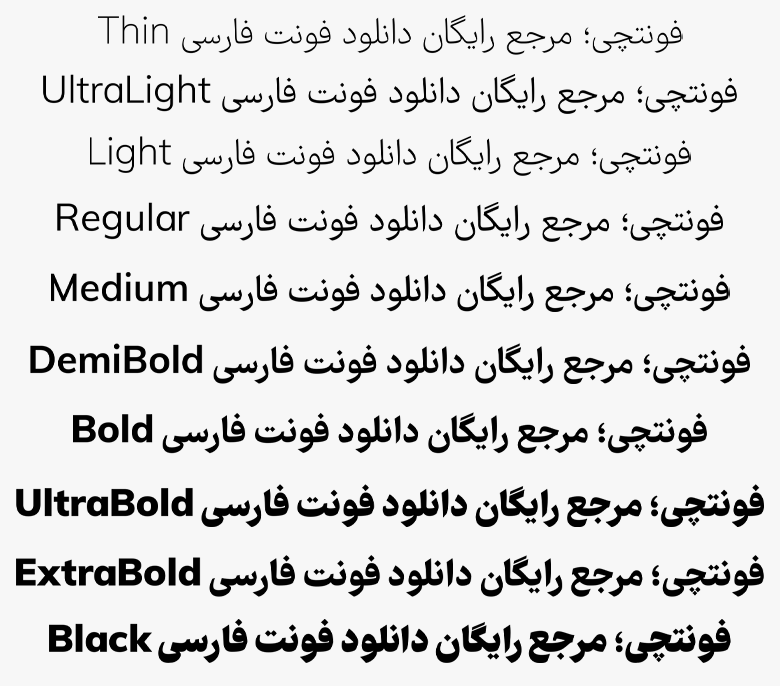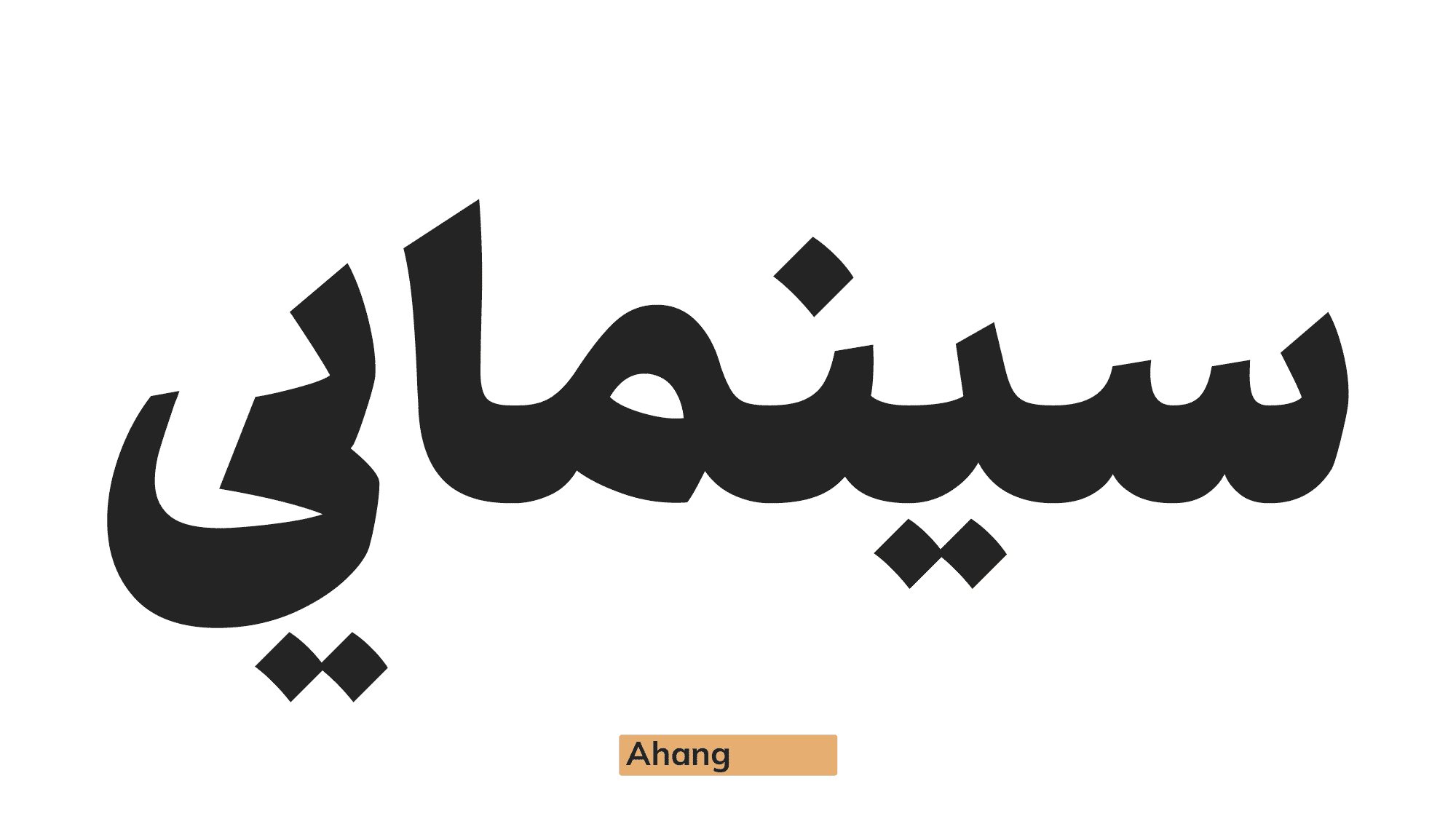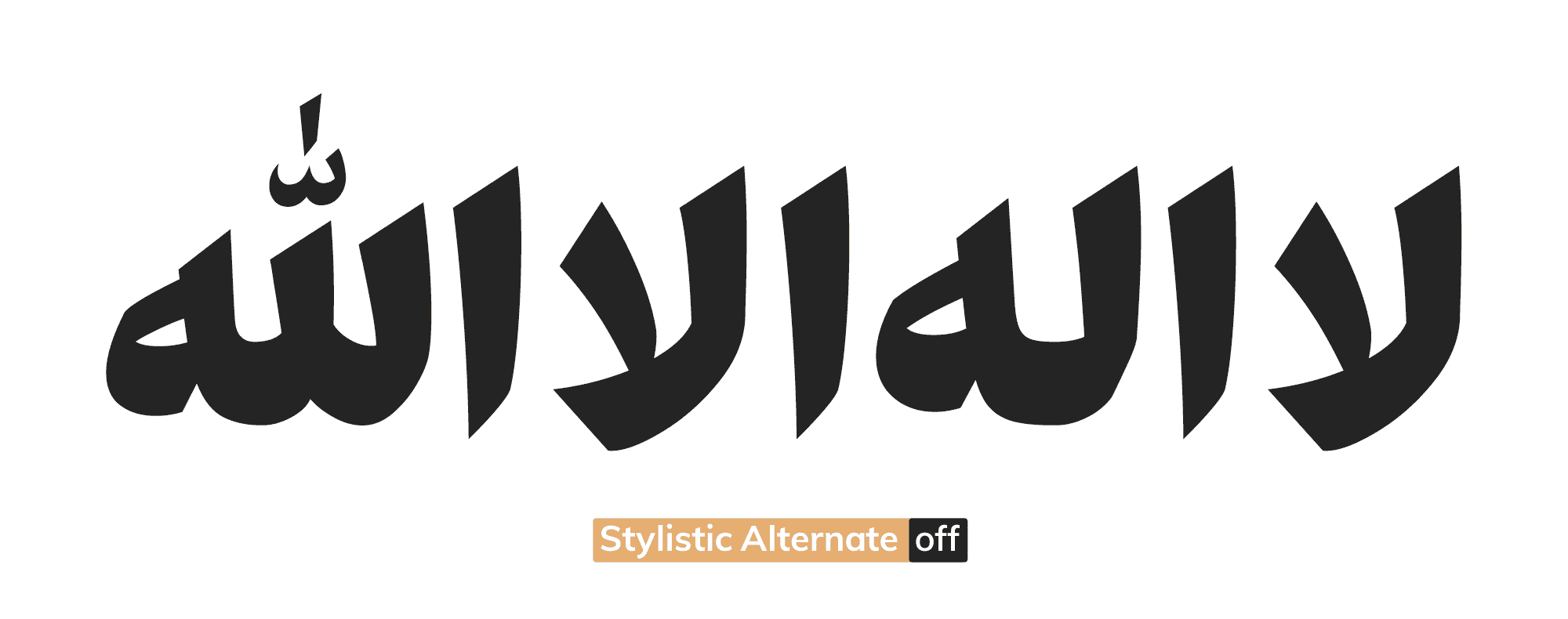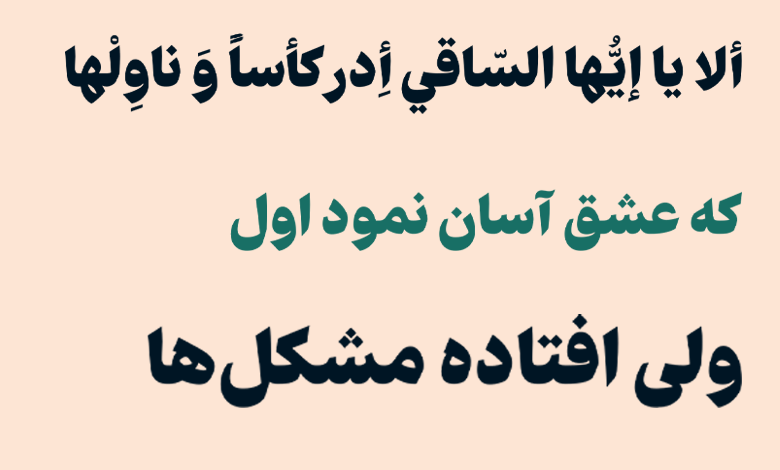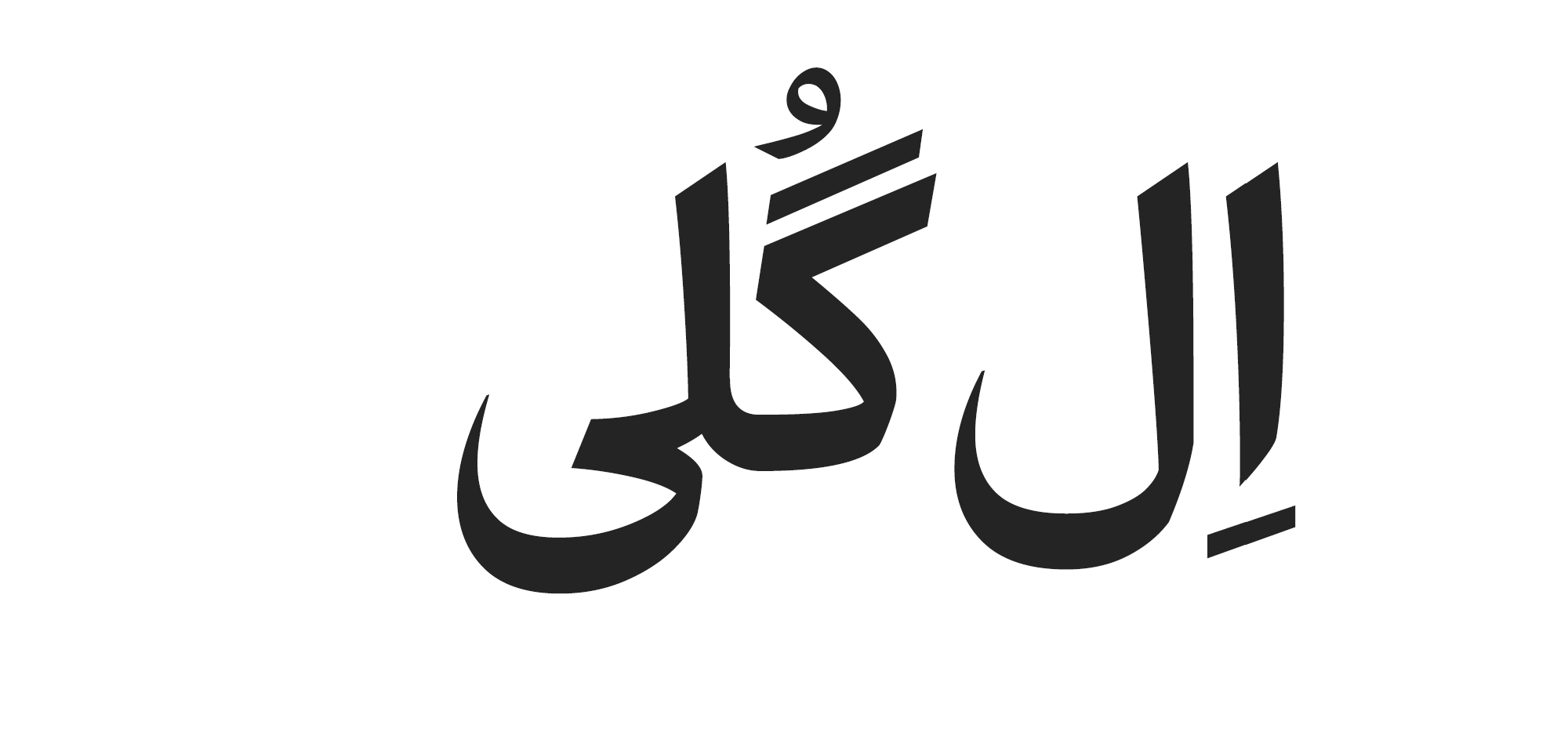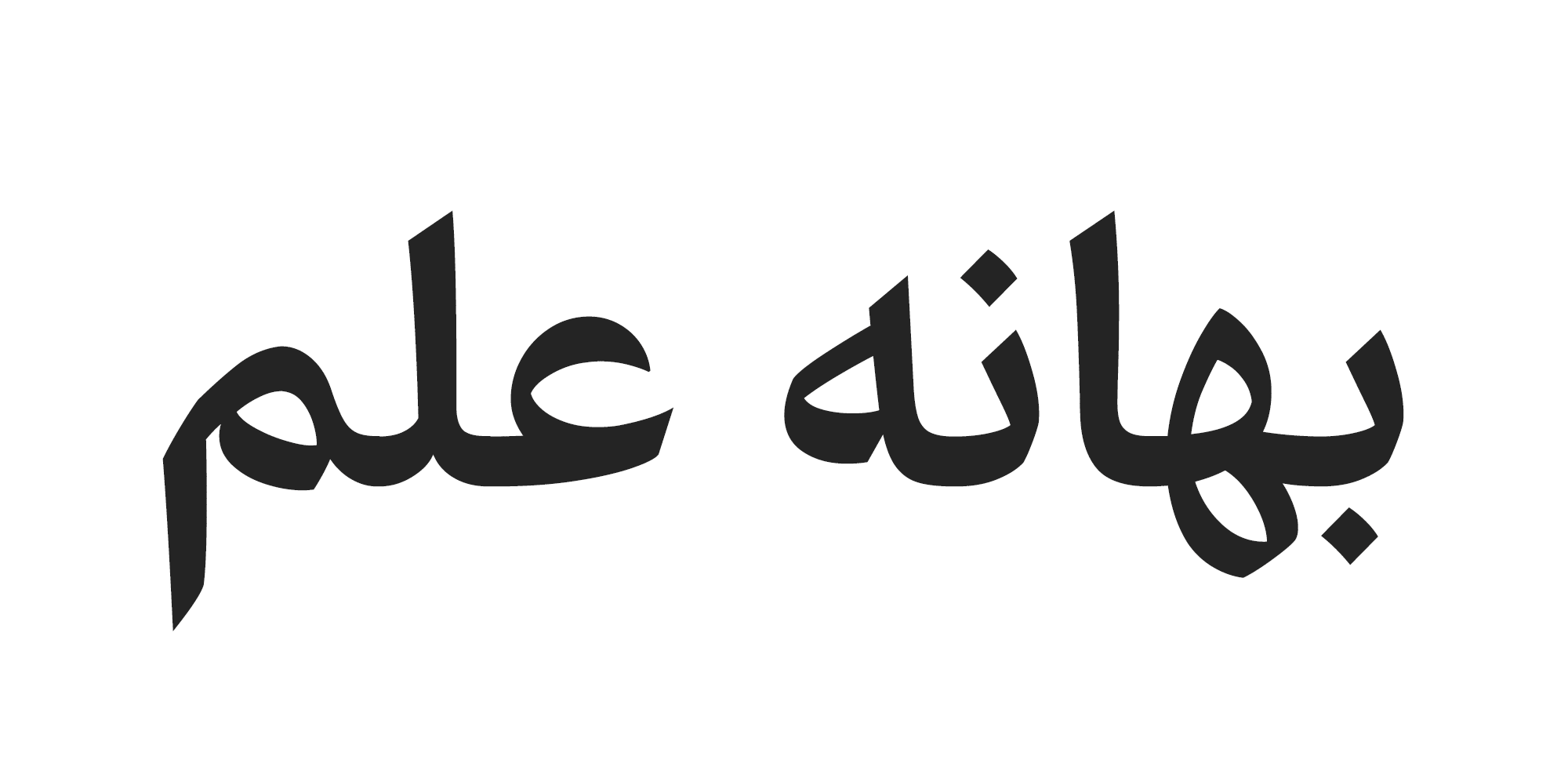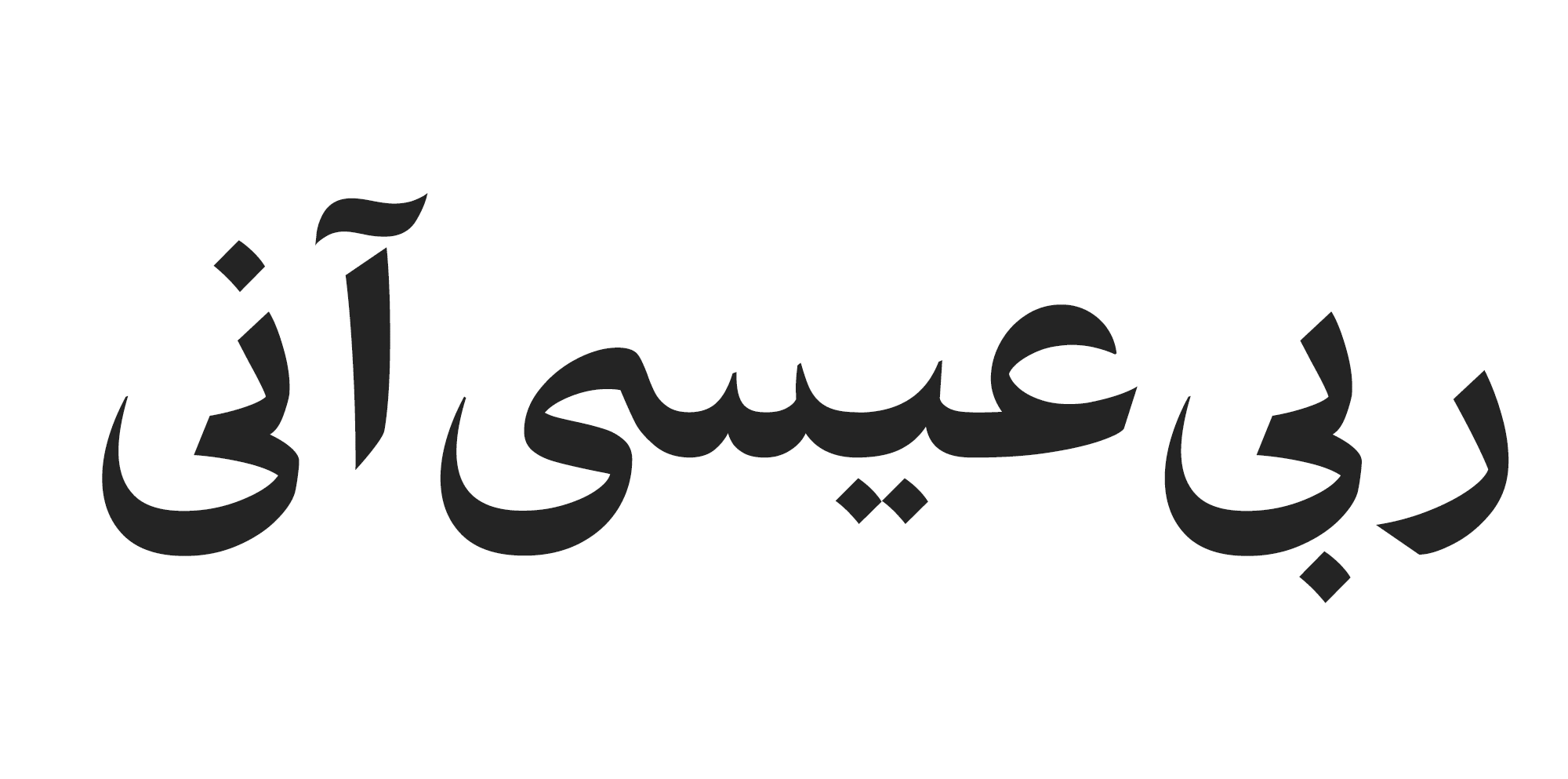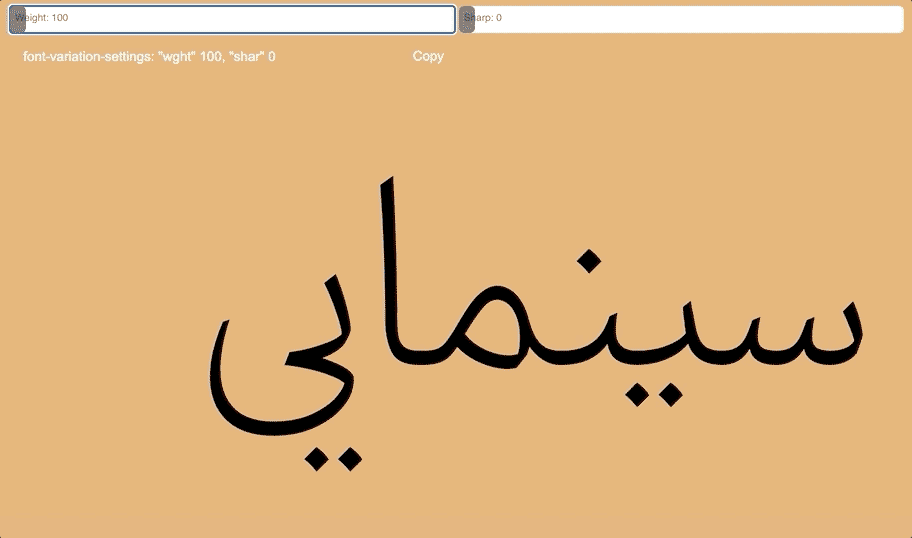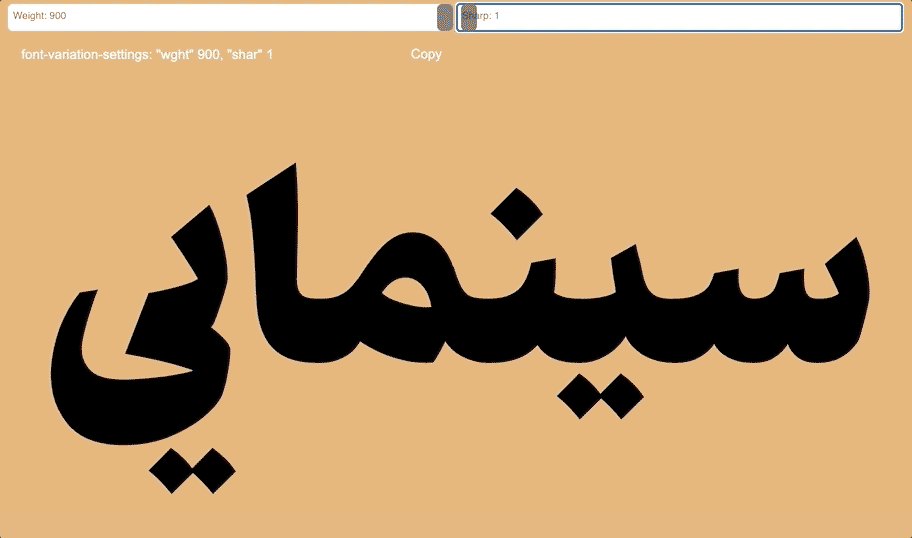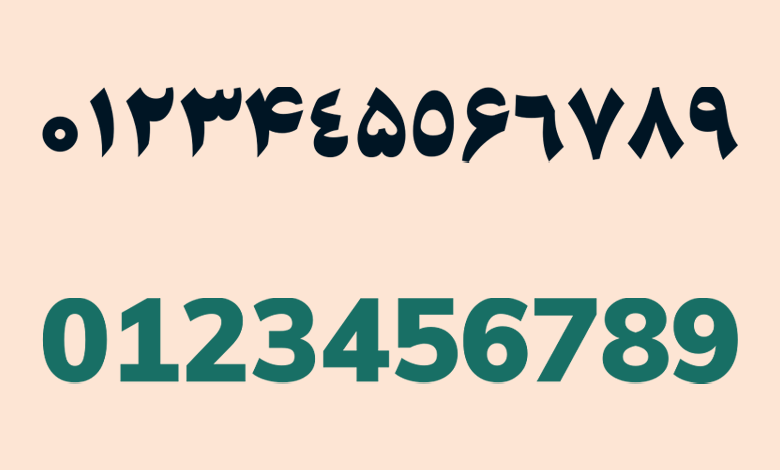
فونت آهنگ (Ahang)
فونت آهنگ (به انگلیسی: Ahang) یکی دیگر از فونتهایی است که توسط مسلم ابراهیمی طراحی شده است. این فونت هم مشابه سایر فونتهای این طراح دارای تنوع وزنی و استایل متنوعی است که میتوانید از آن به عنوان یک فونت متن برای متون طولانی در موارد مختلف صنایع چاپ، وب فونت، کاتالوگ و هر چیزی که دارای متنهای طولانی باشد استفاده کنید.
فونت آهنگ بر پایه خط نسخ طراحی شده که الهام گرفته از فونت فرهنگ است؛ اما با این تفاوت که در این فونت به جای تاثیرپذیری بیشتر از متون مطبوعات، از خوشنویسی دو خط نسخ و ثلث بهصورت ترکیبی الهام گرفته شده است تا در مجموع شاهد فونتی باشیم که هر دو این ترکیبات را در خود دارد.
در ادامه این نوشته از سایت فونتچی به نقد و بررسی فونت آهن خواهیم پرداخت؛ فونتی که جدا از تنوع وزنی ۱۰ تایی خود، امکانات مختلفی را از نظر استفاده از ترکیبات جایگزین، طرههای تزئینی، نسخه وریبل، هم عرض کردن اعداد و نقاط و بسیاری ویژگی دیگر را در خود دارد.
بررسی و دانلود فونت آهنگ (Ahang)
فونت آهنگ در گروه فونت مناسب متن قرار دارد که میتوانید در متون طولانی، بهویژه در وب فونت از این فونت استفاده کنید. با توجه به پشتیبانی این فونت از ۱۰ وزن مختلف، میتوان از وزنهای سنگین هم برای فونت عنوان استفاده کرد.
اگر به دنبال فونتی بر مبنای خطوط خوشنویسی ثلث و نسخ هستید که در هم تنیده شده و یک سمفونی عالی را اجرا کنند، فونت آهنگ میتواند در لیست اولویتهای شما باشد.
سبک طراحی و وزن فونت آهنگ
این فونت از دو سبک از نظر طراحی پشتیبانی میکند؛ آهنگ معمولی و آهنگ شارء؛ فونت آهنگ شارپ حالتی از سبک دوم این فونت است که زمانی که از نسخه Sharp استفاده کنید، اصطلاحا تغییراتی را در کنتراست فونت لحاظ خواهید کرد.
در فونت آهنگ معمولی دندانهها و انتهای حروف تیز نبوده و همان حالت نرم را مثل هر فونت دیگری دارند. اما وقتی حالت شارپ را فعال کنید، دندانهها و انتهای حروف تیز و برنده خواهند شد.
از این نظر فونت آهنگ دارای دو سبک طراحی است که به شما امکان تغییر کنتراست فونت را خواهد داد. این ویژگی را در نرمافزارهای گرافیکی از طریق تنظیمات opentype میتوانید اعمال کنید و برای استفاده در نسخه وب کافی است از تنظیمات متغیری که برای نسخه وریبل قرار داده شده بهره ببرید.
یکی از قابلیتهایی که در خط خوشنویسی ثلث و نسخ وجود دارد، استفاده از طرههای تزئینی است که روی حروفی مثل «ا، ل، لا، ک، صـ، ط» وجود دارد. در این فونت این قابلیت قرار داده شده که بتوانید از این ویژگی نیز استفاده کنید.
برای استفاده از این حالت کافی است در نرم افزارهای گرافیکی با استفاده از تنظیماتی که در Open Type وجود دارد از حالت Stylistic set استفاده کنید.
پشتیبانی از ۵ زبان مختلف آسیایی و لاتین
فونت فارسی آهنگ محدود به زبان فارسی نبوده و با توجه به اینکه رسم خط فارسی در زبانهای عربی، کردی و اردو نیز وجود دارد از این زبانهای خاورمیانهای و همچنین نسخه مخصوص زبان انگلیسی برای زبانهای لاتین هم پشتیبانی میکند.
ناگفته نماند که در نسخه انگلیسی فونت آهنگ ظاهرا از فونتهای اپن سورس استفاده شده و دارای طراحی اختصاصی نیست.
در نسخههای اردو، عربی و کردی کلیه اعراب و حروف که تفاوتهای جزئی با زبان فارسی دارند در فایل فونت جای گرفته است. برای مثال برای زبان عربی که حروف «ک، ی، ه، ؤ، ئ» دارای تایپ متفاوتی است یا در زبان کردی و اردو که از کاراکترهای تزئینی و اعراب روی حروف استفاده زیادی میشود در این فونت پیادهسازی شده است.
دارای ترکیبات و حروف جایگزین متنوع
ویژگی دیگر فونت آهنگ پشتیبانی از ترکیبات و حروف جایگزین است. به کمک این ویژگی قادر هستید تا برخی حروف و کلمات که دارای تایپ متفاوتی هستند را از ابتدا تا میانه و انتهای کلمات به شکل متمایزی تایپ کرده و نوشته خود را زیباتر کنید.
این ترکیبات جایگزین جدایی از زیبایی به خوانایی متن نیز از این جهت که در متون طولانی کاربر خطوط را گم نکند کمک بسیار زیادی خواهند کرد. یا اینکه برای تاکید روی برخی کلمات کلیدی، در استفاده برای طراحیهای تبلیغاتی میتواند موثر باشد که نام برند را با این ترکیبات بنویسید.
مثلا در تصویر بالا همانطور که میبینید، کلمه «ال گلی» در مجموع به این امکان که حروف «ل، گ، ی» دارای تایپ متفاوتی است، را میتوان در بیش از ۶ حالت مختلف تایپ کرد.
یا در مثال دیگری مثل تصویر زیر میتوانید حروف «ه، ع، م» را بسته به اینکه در ابتدا، میانه یا انتهای کلمات باشند در چند حالت مختلف تایپ کنید. حرف «ع» که در اینجا دارای دو ساختار است، با ترکیب در حرف جایگزین میم میتواند ظاهر بسیار متفاوتی را از حالت معمولی فونت در اختیار قرار دهد.
در زبان فارسی و در تمامی فونتها حرف «ی» بیشترین ترکیب و ساختار را از نظر حروف جایگزین دارد. در تصویر زیر همانطور که میبینید در فونت فرهنگ امکان تایپ این حرف را در ۵ حالت مختلف در انتها کلمات خواهید داشت.
این ترکیبات جایگزین محدود به حروف بالا نبوده و در حروف و ترکیبات متعدد دیگری هم قابل استفاده هستند. همچنین این ترکیبات جدا از زبان فارسی، در زبان اردو و کردی هم قابل استفاده هستند؛ خصوصا اینکه در زبان اردو ترکیباتی در حروف «ﮧ ﮩ»مدل نستعلیق و «ے» معکوس به صورت پیشفرض وجود دارد.
فونت متغیر آهنگ با امکان تغییر وزن و کنتراست
فونت وریبل آهنگ یا همان نسخه متغیر این فونت دیگر ویژگی است که این فونت دارد و بر خلاف بیشتر فونتها که فقط قابلیت تغییر وزن را دارند، در این فونت امکان تغییر کنتراست فونت را از نظر دندانهها و تیزی حروف نیز در اختیار خواهید داشت.